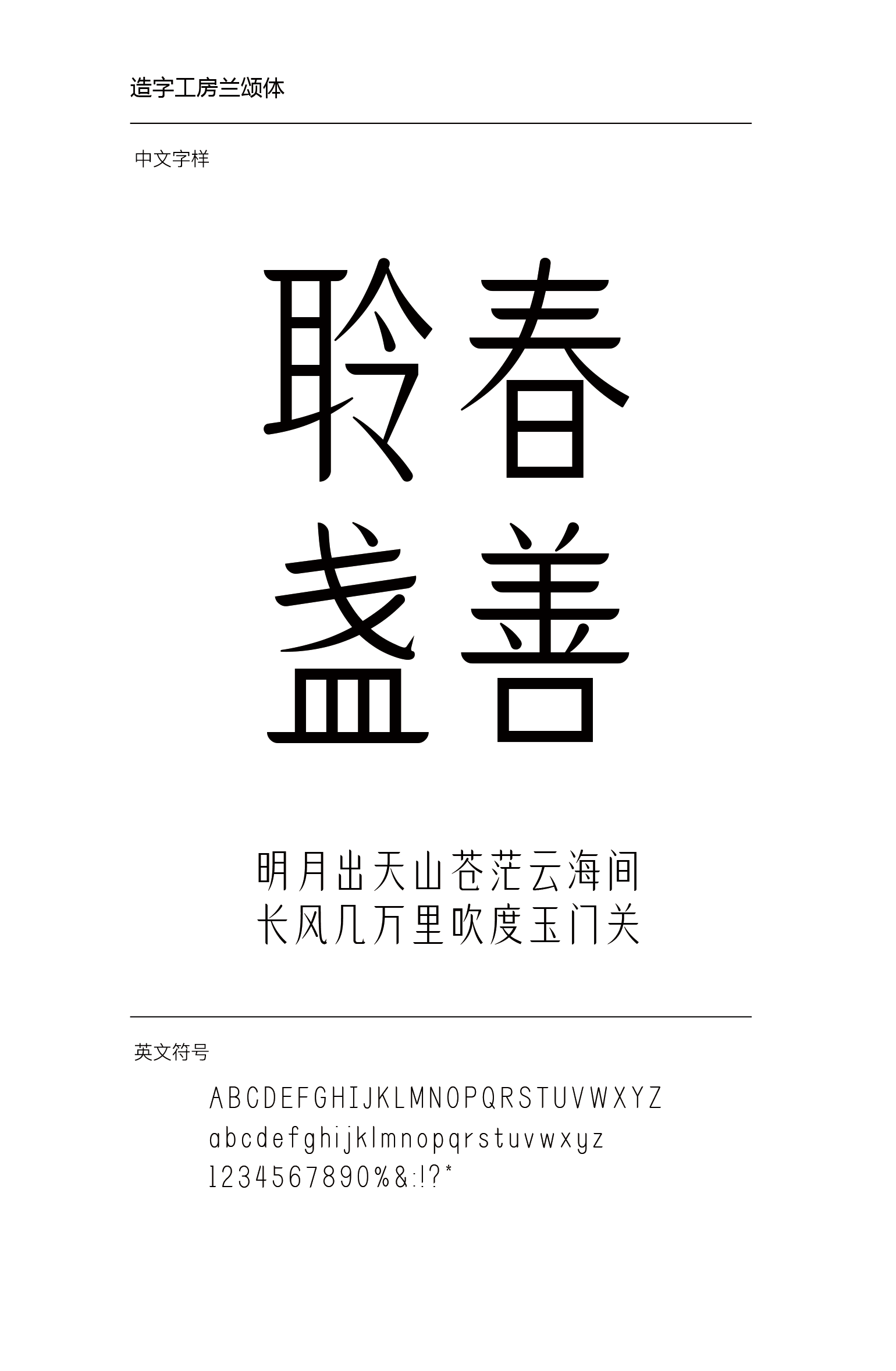
造字工房兰颂体 造字工房兰颂体设计说明 造字工房兰颂体,笔法瘦劲修睿、圆润舒展,其笔画停匀秀美,字身紧凑,结体平稳,章法疏密有致。笔触流畅自然,清新脱俗,尖峰利落,令其平添一份含蓄妍媚的女性之美,清新明快,爽心悦目。此款字体适用于时尚行业,主作标题与副标题之用 ,有着极强的应用空间。 本字体为简体字库,采用OpenType/CID格式,Adobe-GB1-5编码。基于中华人民共和国GB2312-80字符集标准,另按需添加101个汉字。共收容字数6864CJK汉字,ASCII常用字符100个。 下载地址 点击下载